빙그레 무료 서체, 귀여운 디자인과 다양한 활용법
빙그레에서 제공하는 무료 서체들은 따뜻하고 유쾌한 디자인으로 많은 사랑을 받고 있습니다. 개인적인 용도부터 상업적인 용도까지 다양한 활용이 가능하며, 특히 블로그나 디자인 분야에서 인기를 끌고 있습니다.
빙그레 무료 서체 종류
빙그레체: 빙그레 바나나맛 우유 포장지를 모티브로 한 둥글고 귀여운 글꼴입니다.
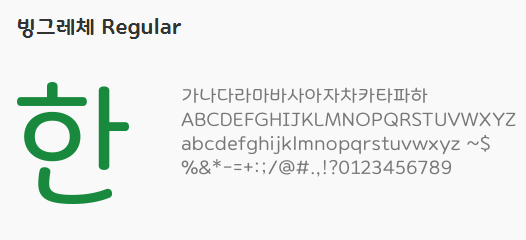
빙그레체Ⅱ: 빙그레체보다 다소 깔끔하고 세련된 느낌의 글꼴입니다.
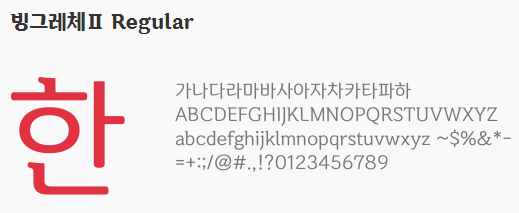
빙그레 따옴체: 따옴표 모양으로 디자인된 독특한 글꼴입니다.
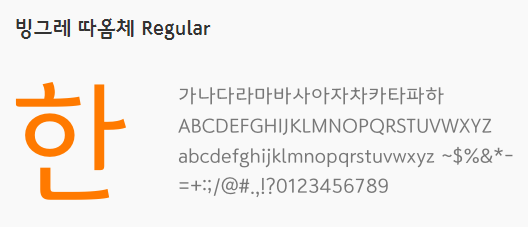
빙그레 메로나체: 빙그레 메로나 아이스크림 포장지를 모티브로 한 시원하고 상큼한 글꼴입니다.
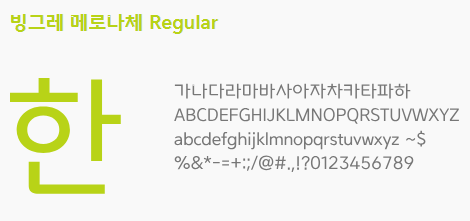
빙그레 싸만코체: 빙그레 싸만코 바를 모티브로 한 굵고 즐거운 느낌의 글꼴입니다.
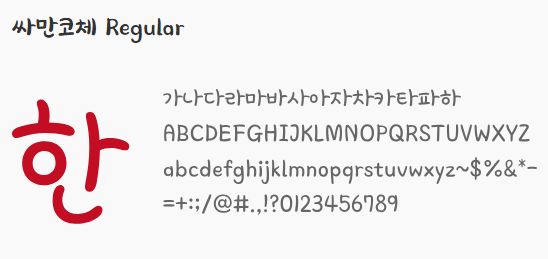
빙그레 무료 서체 특징
- 한글과 영문 모두 지원: 한글과 영문을 모두 지원하여 다양한 용도로 활용할 수 있습니다.
빙그레 무료 서체 활용 방법
- 블로그 및 홈페이지: 빙그레 무료 서체를 사용하여 블로그나 홈페이지의 디자인을 더욱 개성 있게 만들 수 있습니다.
- 포스터 및 디자인: 포스터, 배너, 명함 등 다양한 디자인에 빙그레 무료 서체를 활용하여 독특한 분위기를 연출할 수 있습니다.
- 프레젠테이션: 프레젠테이션 자료에 빙그레 무료 서체를 사용하면 청중에게 친근하고 즐거운 느낌을 줄 수 있습니다.
- 개인 용도: 개인적인 용도로 메모, 일기, 편지 등을 작성할 때 빙그레 무료 서체를 사용하여 개성을 더할 수 있습니다.